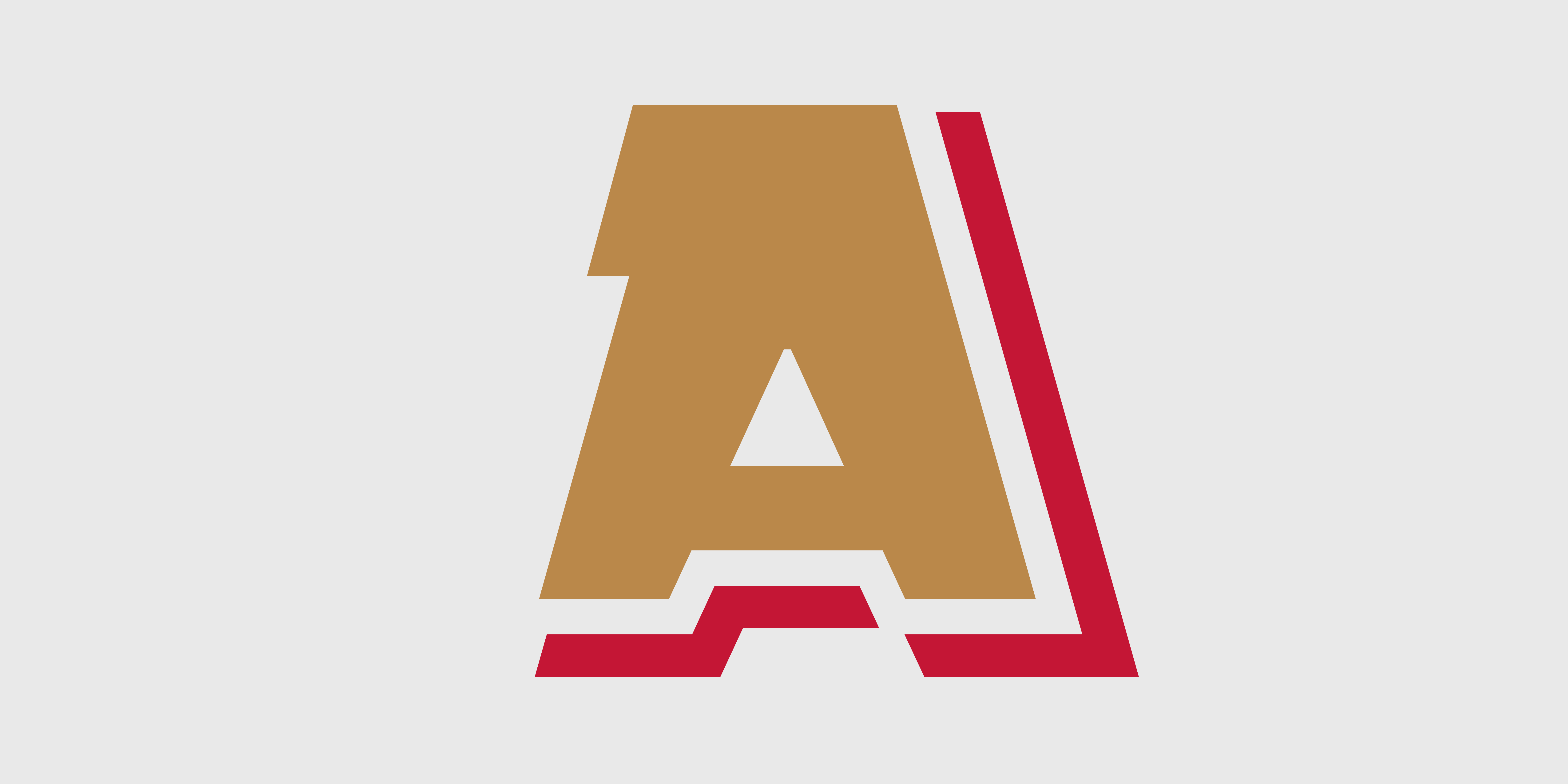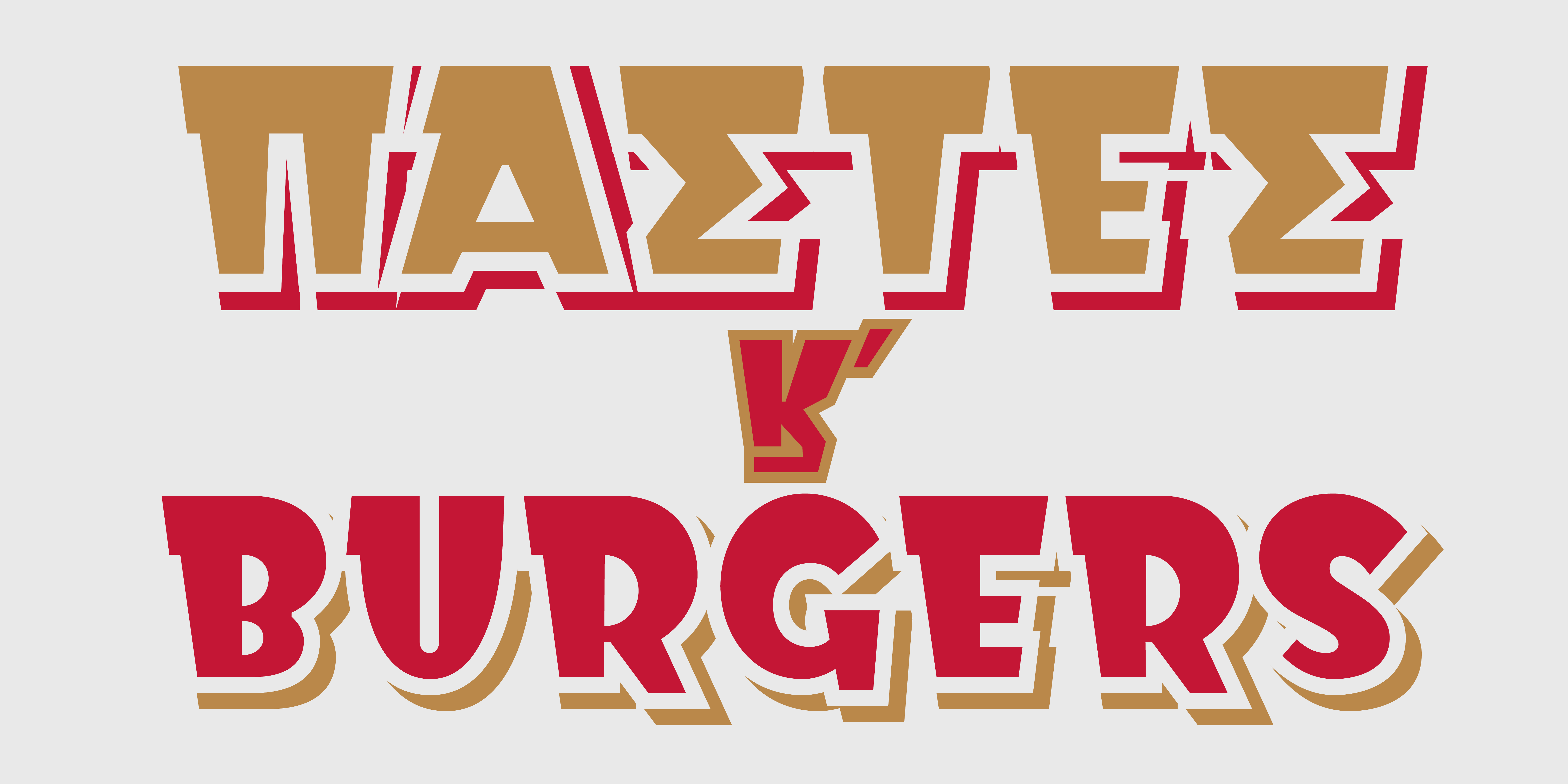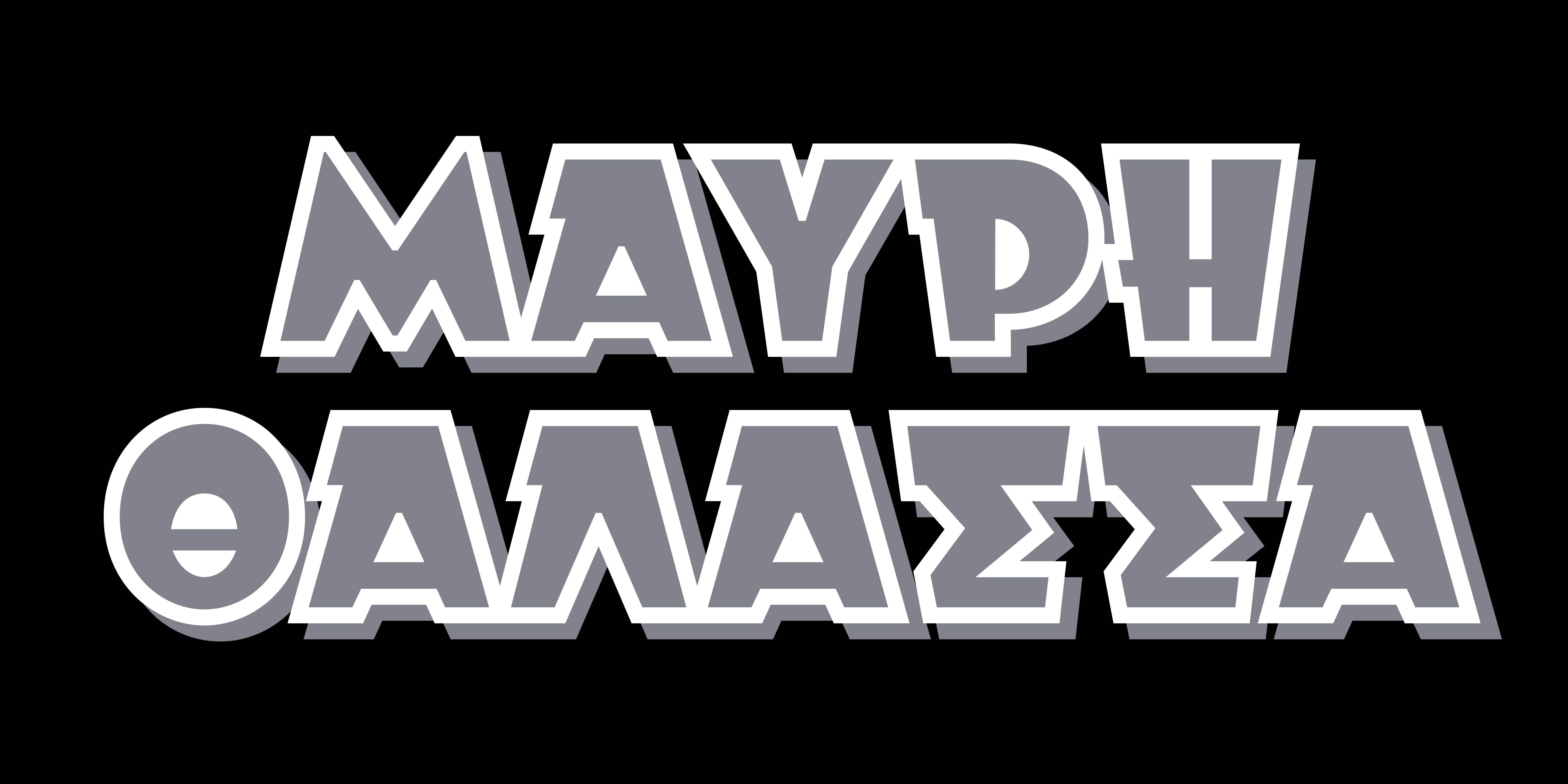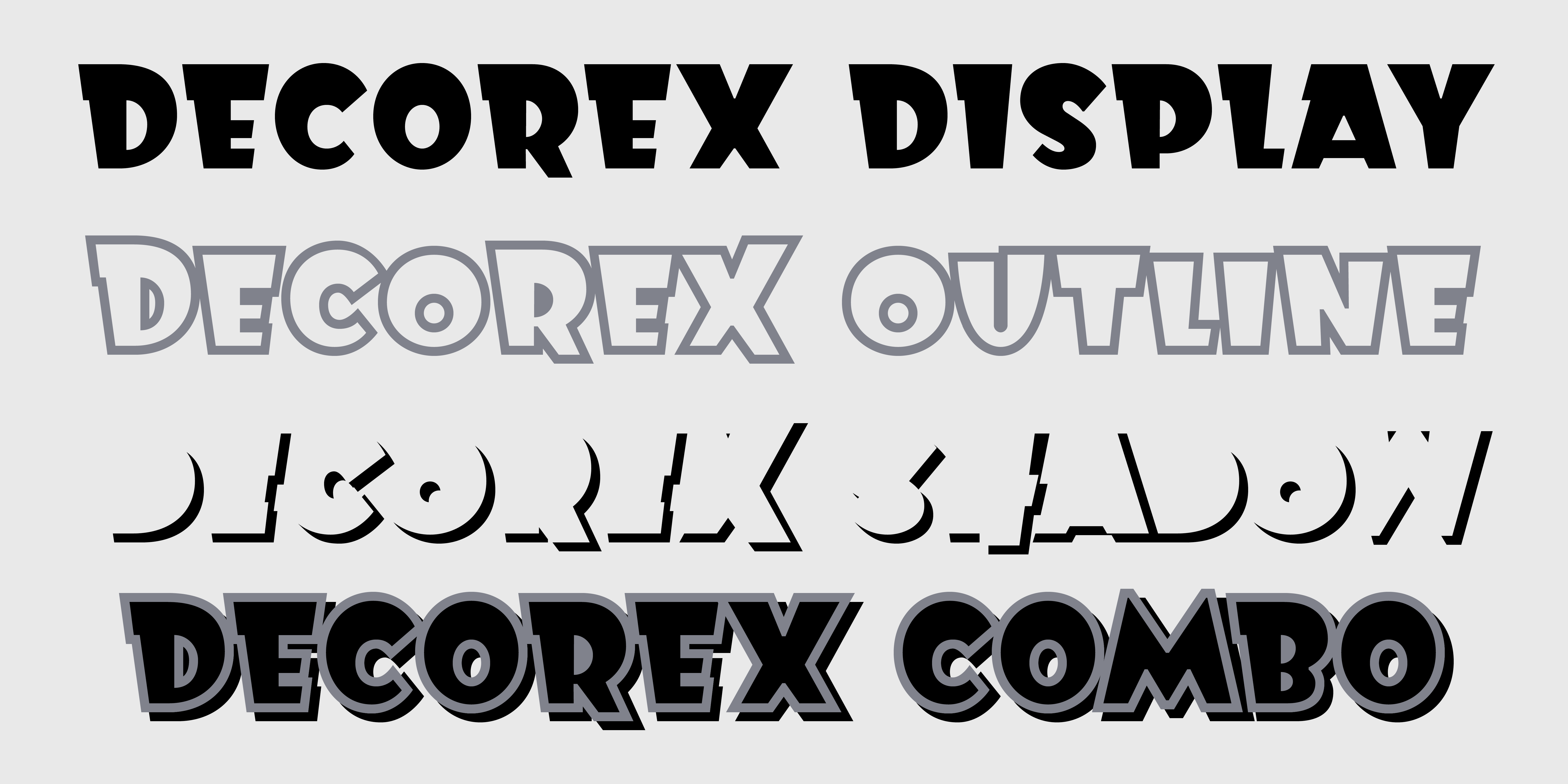
Decorex
Η CF Decorex, είναι μια κεφαλαιογράμματη σειρά τίτλων σε σφηνοειδή φόρμα, η οποία σχεδιάστηκε με αφετηρία την επιγραφή ενός καταστήματος στην πόλη της Καβάλας (η επιγραφή είναι ζωγραφισμένη στο χέρι και διακρίνεται η υπογραφή «ΜΑΝΙΟΣ»). Αυτός ο τύπος γράμματος εντοπίζεται συχνά σε διάφορες επιγραφές καταστημάτων και εταιρικά λογότυπα, με πιο χαρακτηριστικό αυτό της εταιρίας «ΙΖΟΛΑ». Η CF Decorex αποτελείται από τρία στυλ: κανονικό, με περίγραμμα και σκιά. Εκτός από κεφαλαία, περιλαμβάνει μικρά κεφαλαία – ελαφρώς παραμετροποιημένα και με μια τυχαιότητα στο ύψος.